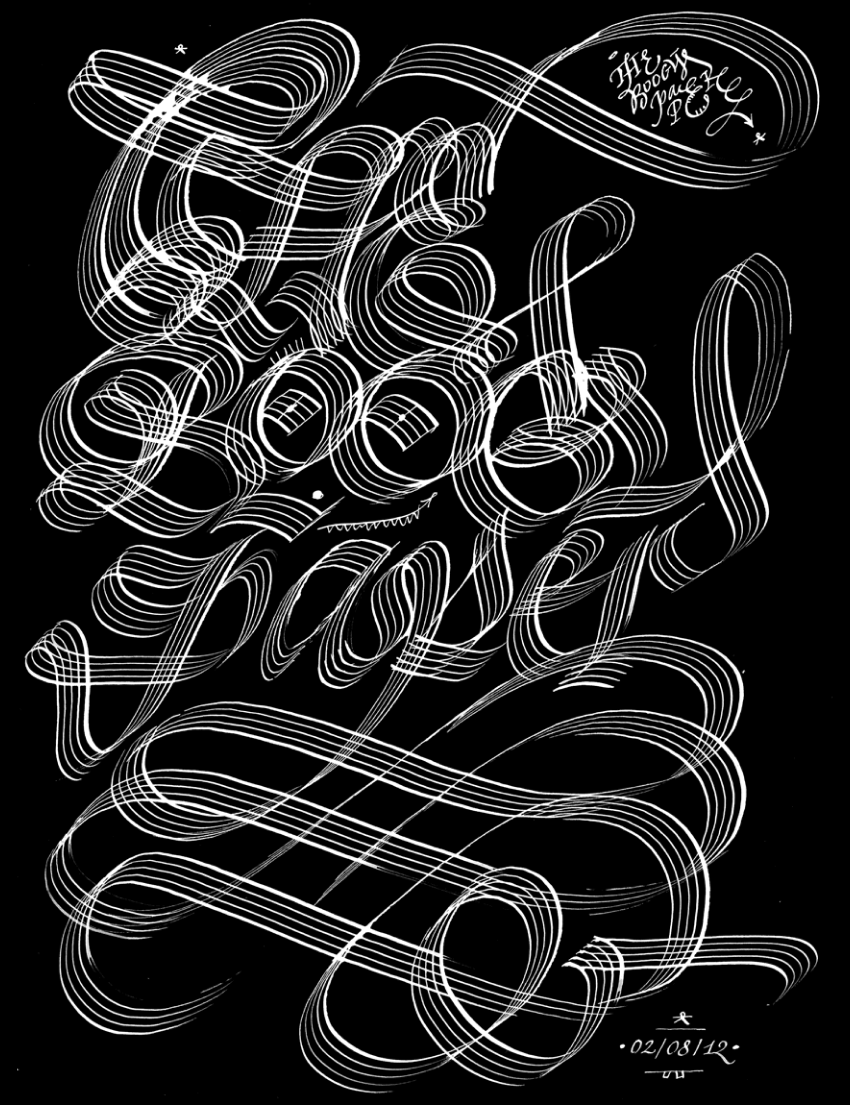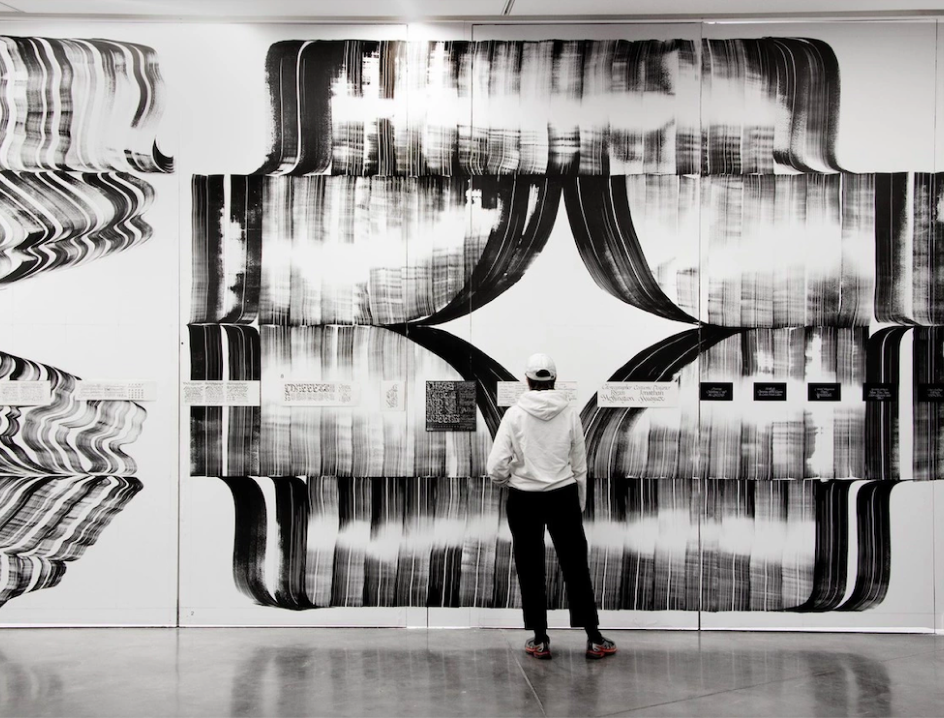
Аделина Шайдуллина: Что значит Boogy в твоём нике? Это танец? Или отсылка к бугимену?
Жюльен Прие: Танец! Это в каком-то смысле цитата из старого французского рэп-трека Boogie Man группы NTM . В институте я придумывал журналы и делал для них обложки, один из таких журналов я назвал The Boogy Paper. А потом я начал регистрироваться в Инстаграме и обнаружил, что там уже есть человек по имени Жюльен
Каллиграфия для журнала Boogy Paper, 2014
АШ: Хип-хоп, кажется, вообще сильно повлиял на твои работы.
ЖП: Да! До института я слушал только
АШ: То, что ты делаешь, в интернете называют словом typexpressionism. Можешь рассказать, что это за термин и откуда он взялся?
ЖП: Его придумал критик Стивен Хеллер, и мне кажется, это очень хорошее слово. Люди часто говорят, что мои
Да, граффити — это экспрессивный жанр, да, все с ним знакомы, и он на многих повлиял. Но это не значит, что все, кто делает экспрессивную
Зин Boogy Paper, 2023
ЖП: Ещё когда ты студент, твои шрифты должны быть очень аккуратными и читабельными. Но ведь на самом деле
Например, мы с моим коллегой по коллективу
High on Type — коллектив художников, дизайнеров и каллиграфов, в котором Жюльен участвует с 2015 года High on Type Винсентом де Буром начали заниматься каллиграфией просто потому, что любили рисовать
Инсталляция и перформанс «MOD-de Knoop» Винсента де Бура, 2021. Изображение: Робин Майер
Серия «One Stroke Painting» Винсента де Бура, 2019. Изображение: Logman Gallery
АШ: Boogy Brut — это исследование спектра читабельности, о котором ты говоришь?
ЖП: Да. Boogie Brut — это такой мост, который проходит через весь спектр. Нам с Йоанном Мине Йоанн Мине — шрифтовой дизайнер, соавтор Boogie Brut было важно, чтобы все шрифты коллекции хорошо работали друг с другом и чтобы зрителю было понятно, что у всех этих начертаний одни и те же корни, одна и та же графическая идея.
Спеисмен Boogy Brut, 2020. Дизайн: Марк Смита, Бенуа Сантьяр
Стикеры Boogy Bruts
АШ: Ты работал с очень разными материалами. Рисовал на одежде, четырёхметровых стенах и даже детском планшете для обучения письму. На чём ещё тебе было бы интересно порисовать?
ЖП: Мне вообще нравится исследовать новые материалы. Иногда я просто нахожу что-то
Не знаю, каким будет следующий инструмент. Но сейчас я заказал из Японии несколько конструкторов, из которых можно собирать роботов. Может, я сделаю какие-нибудь деколи, которые будут классно работать на нём, или даже придумаю новый шрифт специально для этого конструктора.
Коллекция одежды Martès × Boogy Brut
АШ: У тебя недавно была выставка в Эшироле. Расскажи, как кураторы работают с каллиграфами? Это похоже на то, как они взаимодействуют с современными художниками?
ЖП: Совсем не похоже. Мне вообще показалось, что сотрудники музея, который меня пригласил, плохо понимали, чем я занимаюсь. Поэтому мне пришлось пригласить своего куратора и своего графического дизайнера, и мы сделали всё так, как считали нужным. Я рад, что выставка случилась, но делать по выставке в месяц, как большинство художников, я бы, конечно, не хотел.
АШ: Думаешь, шрифтовым дизайнерам важно выставляться в музеях?
ЖП: Да. И думаю, моя выставка была полезной не только для меня, но и для зрителей. Мне было важно сделать её в государственном
У выставки была очень простая концепция: у нас были буквы во всю стену, на которые нужно было смотреть с большого расстояния, а поверх них были наклеены маленькие принты, к которым нужно было подходить очень близко. Мы хотели показать, что в любой дисциплине есть пространство для разных точек зрения, разных способов смотреть на одну и ту же вещь.
Выставка «Boogy Show», 2024
АШ: Шрифтовые дизайнеры часто жалуются, что в шрифтовом дизайне нет критики.
ЖП: Во-первых, дизайнеры, которые в основном критикуют друг друга в инстаграме, далеко не всегда добрые и хорошие люди. Во-вторых, выпускать шрифт вообще очень сложно. Для тебя как для автора это большое событие, но его почти никто не замечает. Самый большой критик моих
Быть дизайнером сложно. Но быть художником тоже сложно. Делать
АШ: Обычно ты устал и разочарован.
ЖП: Да. Когда выпускаешь шрифт, он с тобой навсегда. Ты можешь доделать его, поправить и выпустить снова. А у выставки есть определённая продолжительность, и её определяешь не ты. В выставках вообще много параметров, которые определяешь не ты.
Например, у меня была проблема с одним из музейных медиаторов. Я зашёл и увидел, что он ведёт экскурсию и говорит, что я уличный художник. И я очень расстроился, потому что почувствовал, что сотрудники музея не разобрались в том, что я делаю, даже несмотря на то, что везде были экспликации, и я много раз объяснял им концепцию выставки. Я знаю, что медиатор не хотел меня обидеть, но мне было неприятно слышать, как он назвал меня уличным художником.
Place Жюльена Прие, 2024
Эскизы шрифта Place
АШ: В карьере каждого шрифтового дизайнера наступает момент, когда он начинает рисовать нейтральный гротеск. Как думаешь, у тебя получится этого избежать?
ЖП: Не уверен, что такой вообще существует. Но прямо сейчас мы вместе с Полом и Кристианом работаем над достаточно спокойным. И это очень сложно, но очень полезно для меня как для дизайнера. И я рад, что делаю такой шрифт именно в Commercial Type.